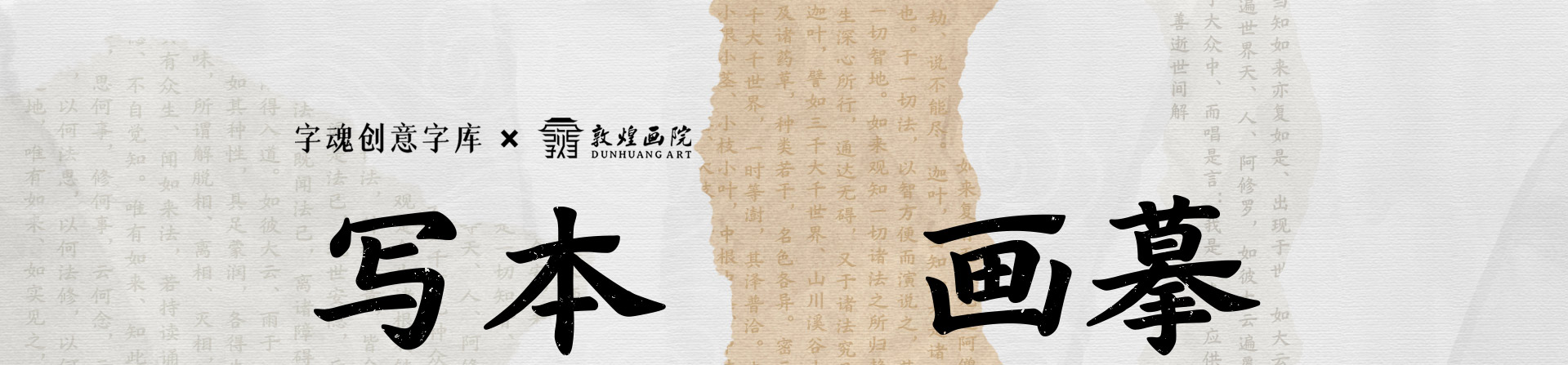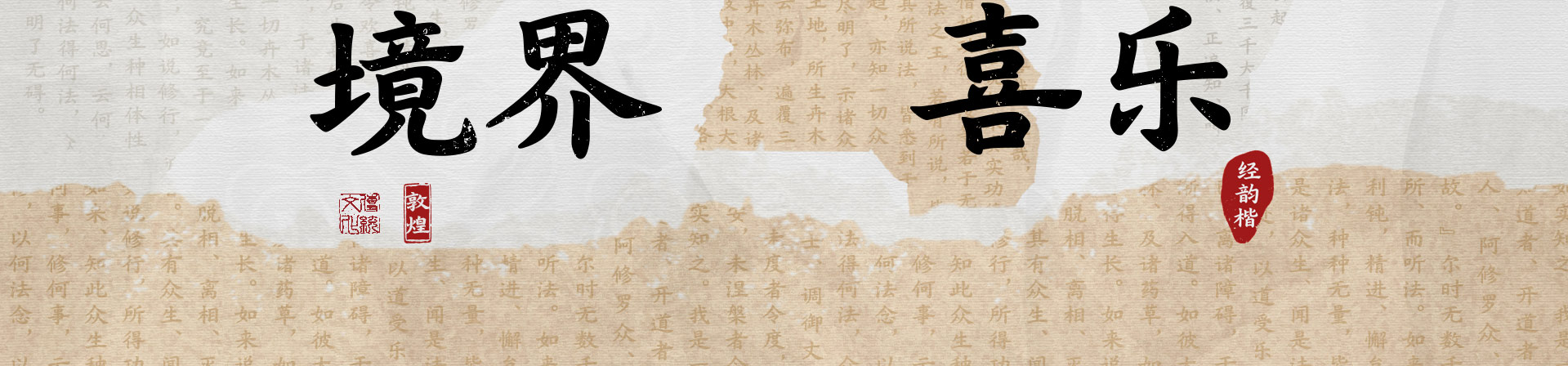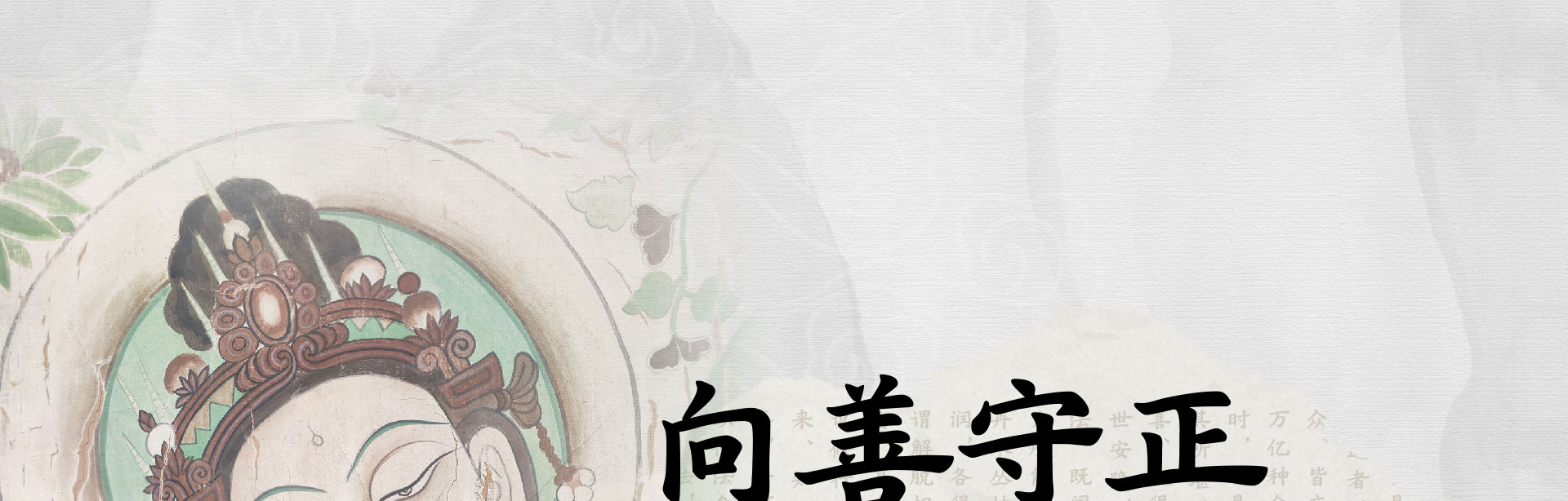
东汉应邵注《汉书》:“敦,大也。煌,盛也。”
敦煌是尘世中的奇迹,也是一片辉煌灿烂的文明圣地。
这里有着举世闻名的两大宝藏,一个被称作敦煌壁画,另一个名为敦煌写本。
画师以纯粹之心,描摹神圣美好的极乐净土;经生以虔诚笔墨,誊抄普渡众生的佛语箴言。
之前,我们汲取壁画之美,打造了,深受大家的喜爱与共鸣。
如今,字魂创意字库再度与敦煌画院携手,
采撷壁画与写本交融的人文艺术之光,共创「字魂敦煌经韵楷」。
于笔画间,看到千年敦煌的无穷魅力。
字魂敦煌经韵楷,以两大敦煌遗产为灵感,将壁画美学、写本底蕴融入字体设计,展现出品牌视觉的多重意蕴:
主体略扁,舒展稳重
呼应敦煌画院开放包容、亲近大众的理念
笔触圆融而不失禅意优美
展现出“向善守正”的美好敦煌精神
字体形态源于经典,又承载以现代设计之风
与“与时俱进”的文化弘扬姿态共振
为精准适配敦煌画院作为文化机构与知名IP,于现代化多元传播场景的应用需求,
设计团队从三大方向进行了字体精细化处理:
通过调整笔画曲线、优化视觉秩序,使品牌字体在线上、线下、
不同载体上的呈现,均保持有严谨而美观的呈现效果。
经由字体设计手法,将品牌温度凝聚在圆融而劲道的一笔一画
间,用视觉语言传递出品牌亲和性。
敦煌画院自1993年建院,三十余年始终专注敦煌艺术文化,可提取
出“传承”“创新”“匠心”等关键词,我们在字面、间距、重心等细节进行了多
次微调,确保能够展现出这些形象特质。